对于设计师而言,在日常的平面和 UI设计中,给字体增加特效一直都是一件恼人的事情。
有些客户直接提出的要什么浮雕、大阴影,你要直接图层样式那么一勾,那真是要有多low有多low。
字体特效非常多,有目的地选取合理的特效是让它们发挥效果的诀窍所在。好的字体排版是不需要辅助就能被识别的,否则这个设计是失败的。
值得一提的是,最好的字体特效往往是润物细无声的,近乎无形,但是对于整个设计在视觉和质感上都有所提升。
但是原创字效总是费时又费力,有没有什么既省事,又不LOW的字效方案呢?
今天分享大师总结了10个优秀的字效方案,为了以后省事,今天先辛苦下,都记牢了!
1. 有目的地运用阴影效果
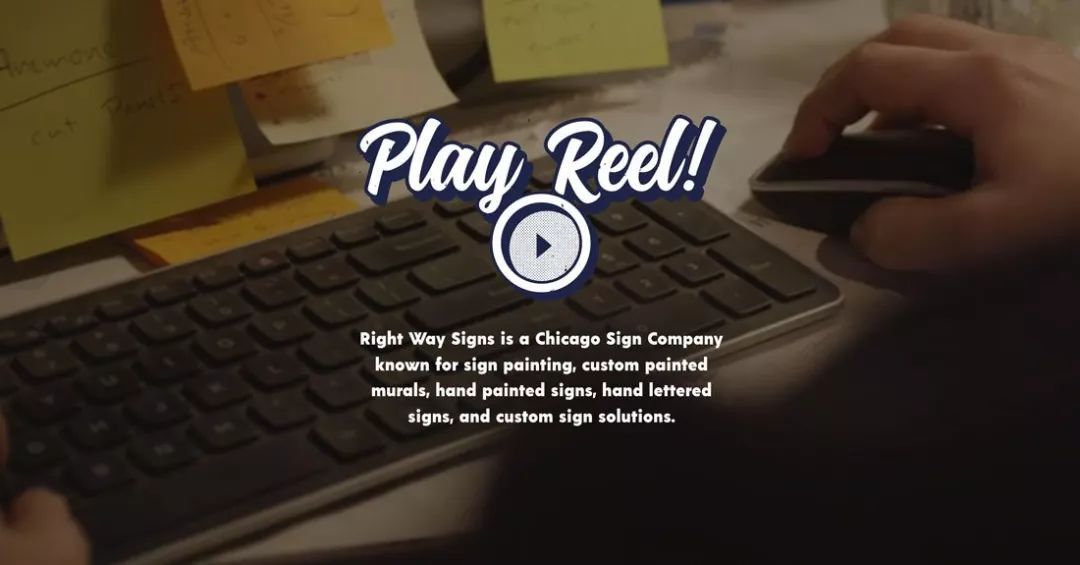
无论你使用什么软件做设计,都不要使用默认的阴影效果,这个经验里面包含了太多血的教训。
正如前文所说,好的阴影特效有着较高的融入度,几乎是「隐形」的。在部署阴影特效的时候,不要为了创建而创建,而是要借助阴影来构建前景文字和背景之间的层次感,这种对比恰到好处即可。
这种「隐形」的阴影设计对于设计师而言通常是不难识别出来的,不过普通用户通常不会太注意到它们。这些柔和的阴影,功能只是用来营造对比。
相对较为硬朗的阴影,会给人以更加复古的感觉,在较粗的、笔触平整的字体背后使用这样的阴影效果会比较好。
2. 使用双重曝光效果
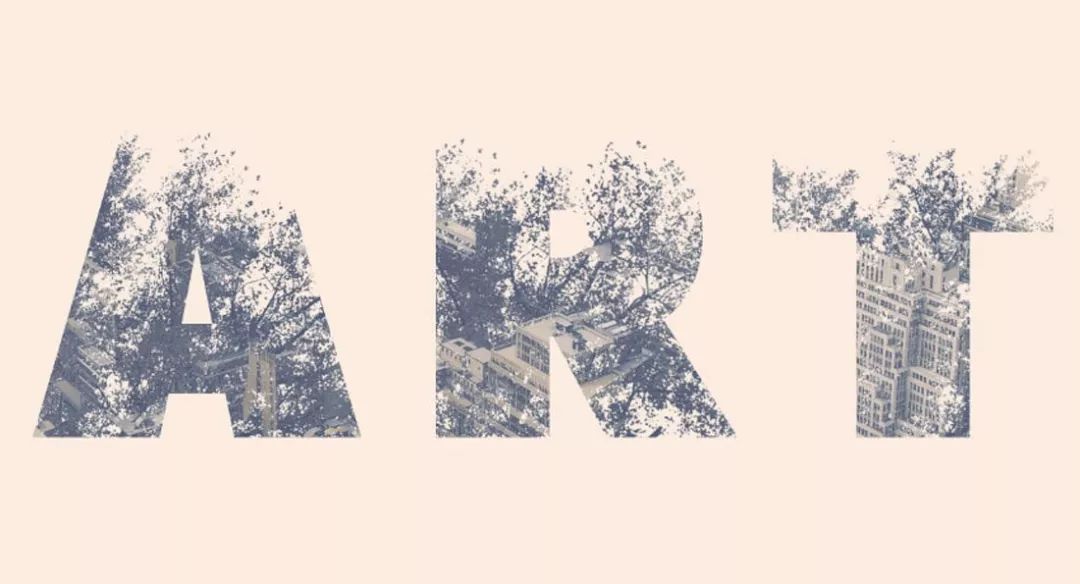
双重曝光效果在网页设计和平面设计当中是非常流行的设计技巧。在文本字体中使用双重曝光效果能够让它看起来复杂而有趣,尤其是在双重曝光的图片选取得比较精妙的时候,效果看起来会非常惊艳。
3. 描边特效
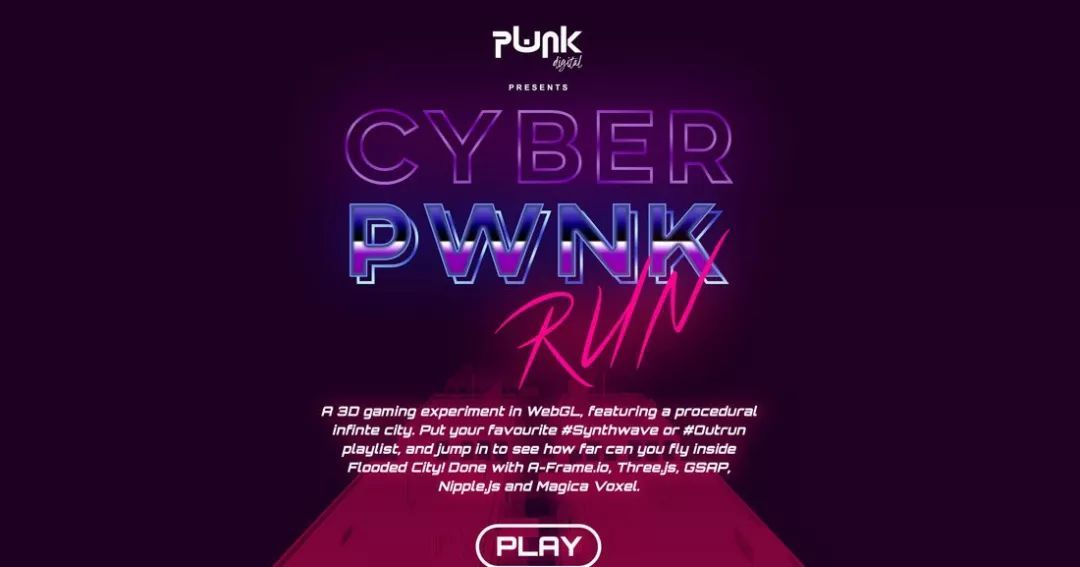
对于较粗的字体使用描边特效,往往能够让字体的轮廓更加清晰,也增加了整体复古的感觉。在上面的案例当中,设计师就借助霓虹色字体和描边特效创造出了独特的氛围。
4. 使用多彩字体
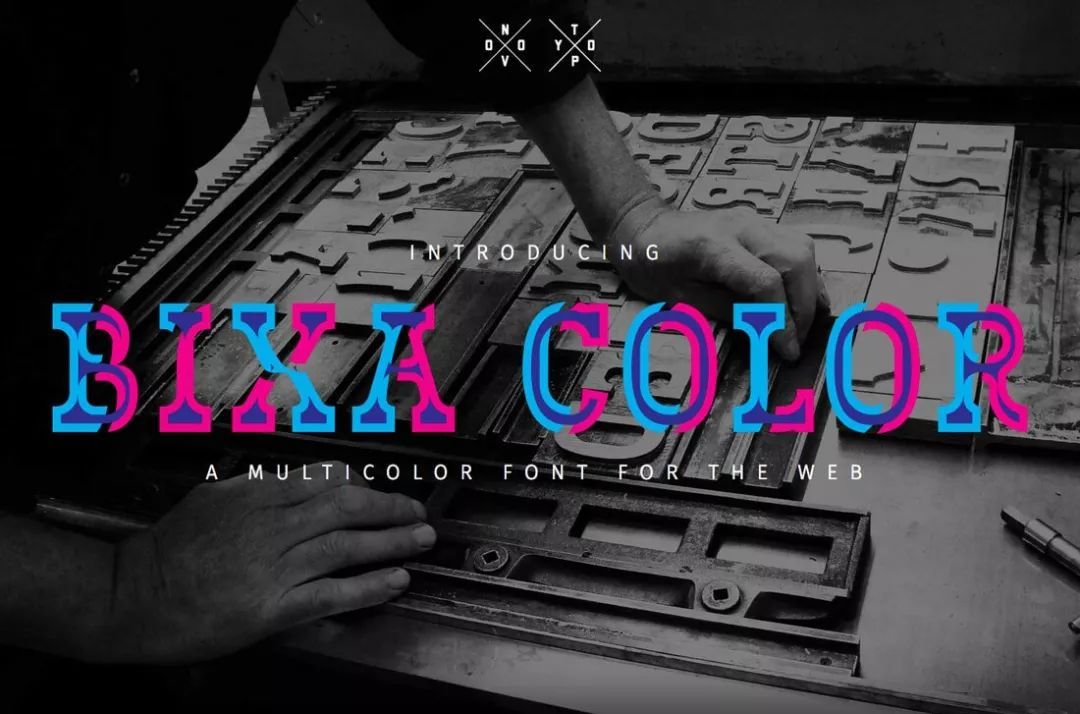
多彩字体本身就包含有多样的色彩属性,甚至含有阴影、渐变、透明度甚至纹理。你可以使用多彩字体来让文本拥有远超传统字体的时髦值。
当大量的色彩共同来构成一套字体的时候,字体本身的视觉吸引力就已经达到极致了。现如今明亮大胆的字体是一种设计趋势,这样的配色本身并不会冒犯用户,因为用户正在越来越适应这样的设计。
当然,在色彩的搭配上需要协调且有目的性。
5. 适当地融入一些动效
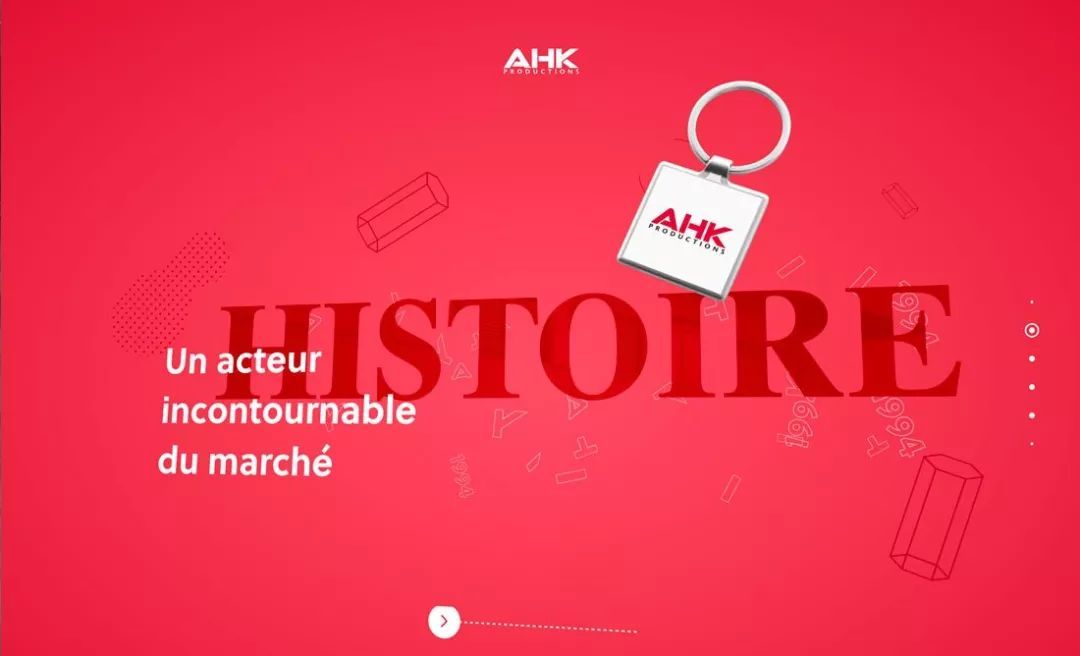
从来都没有规定文本必须是静止的,在网页的文本中加入动效能够提升它的视觉吸引力。
不过,在为文本添加动效的时候,尤其要注意保持文本字体的可读性:
运动轨迹应该是有意识地设计的;
字母的运动不应该太快;
滚动或者自动播放的文本应该可以被停止;
无论屏幕大小,文本内容应该始终保持可读。
6. 模仿一些标志性的元素和特征
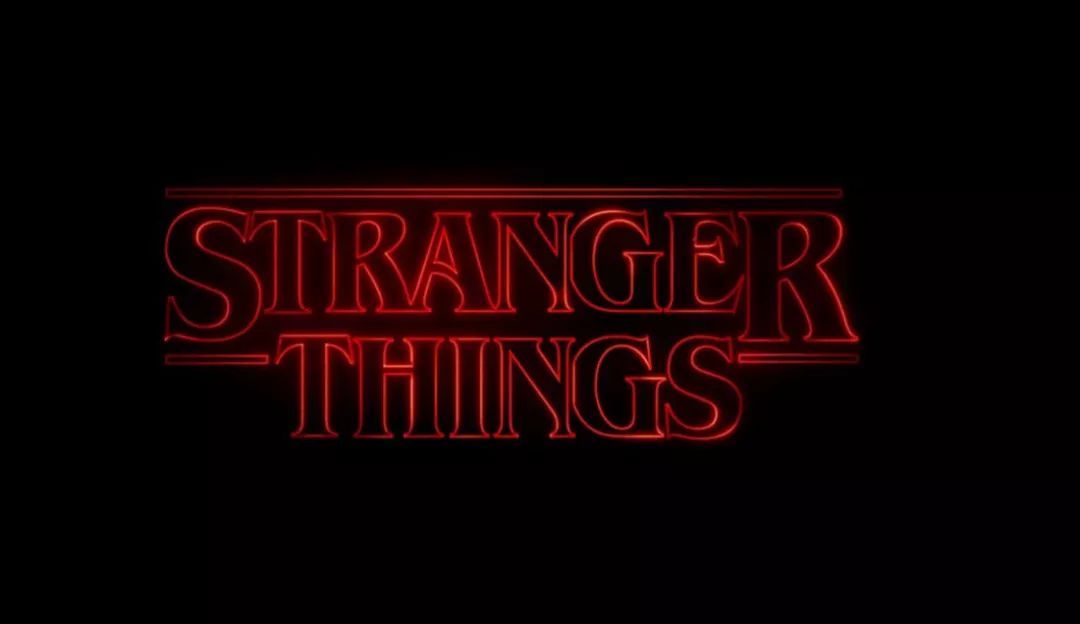
这两年的 Netflix 的热门美剧《怪奇物语》中,就模仿80年代经典的电影,融入了大量当时的元素,创造出让许多影迷共鸣的设计。
最典型的就是霓虹色的运用,充满80年代风情的 LOGO 成为了该剧最具识别度的元素。这种模仿的基础在于近年来80年代复古元素的疯狂流行,以及霓虹色等设计风格的回潮。
在模仿这些标志性的风格和元素的时候,度的把握很重要,恰到好处的模仿让人觉得亲切,而拙劣的复制则会显得很 Low。
7. 引入图形
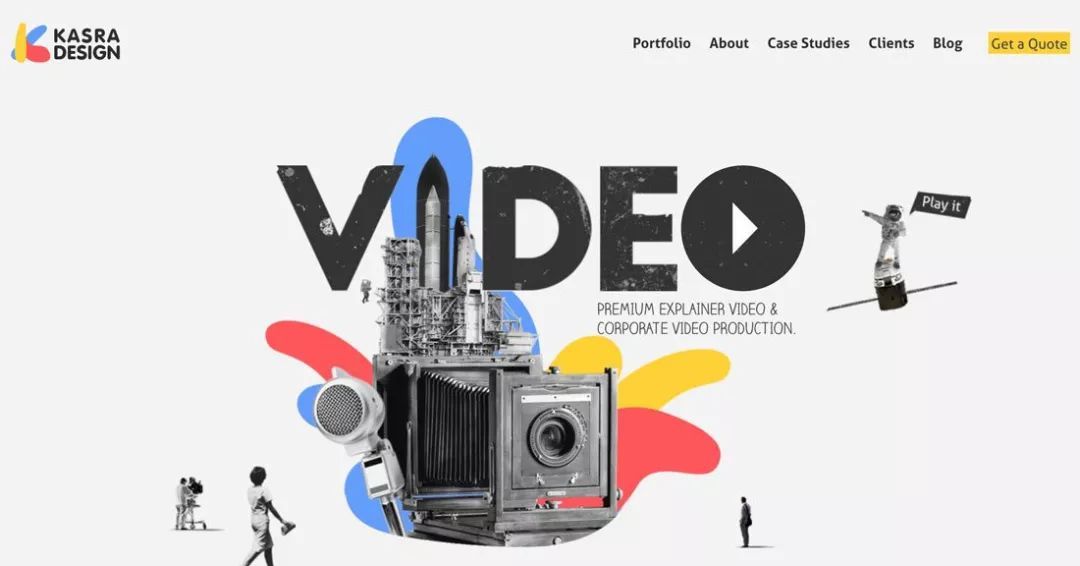
引入图形或者其他的多媒体元素,在文本中加入一些额外的东西,也是不错的手法。使用图形或者其他的元素来替代一个或者多个字母,这样的设计还是很抓人眼球的。
这种技法的诀窍在于,图形的外观要和字母的风格、形状相匹配。很明显,如果不这么做的话,会让内容难以阅读。
在上面的 Kasra Design 的网页当中,视频的触发按钮和图标很好地融合了起来。
8. 增加纹理
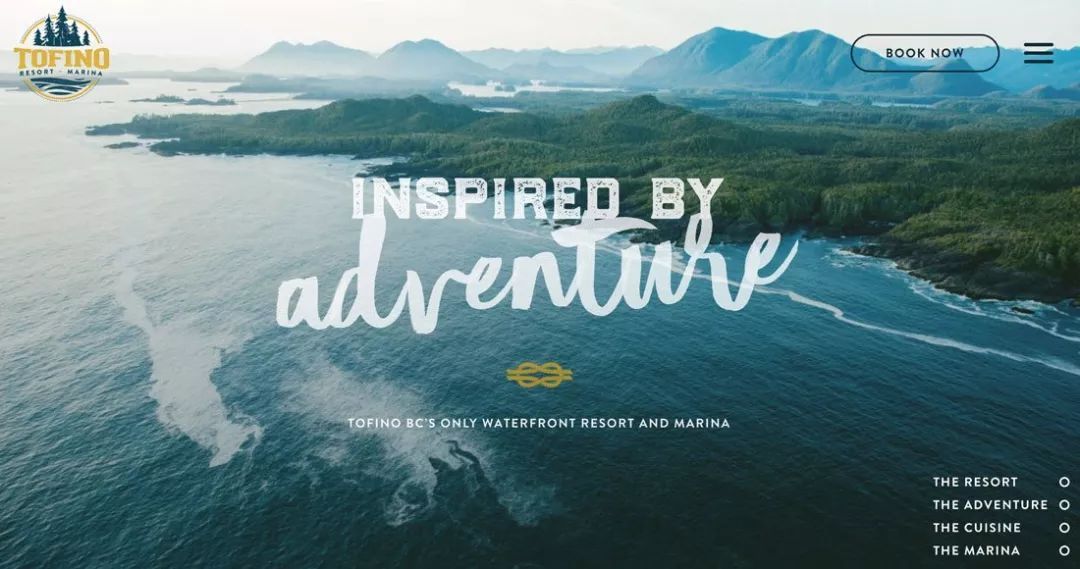
有些字体风格本身就显得复古、粗糙,设计师能够通过自定义增加纹理来强化这种感觉。纹理本身能够让文本更加突出一些,也能够强化文本的质感,营造出独特的氛围。
在上面的案例当中,设计师通过两种不同的方式来赋予文本以纹理:
通过切割出来的细节来赋予文本以纹理;
通过半透明的效果让字体透出背景,从而拥有纹理。
9. 创造自定义的文本字体
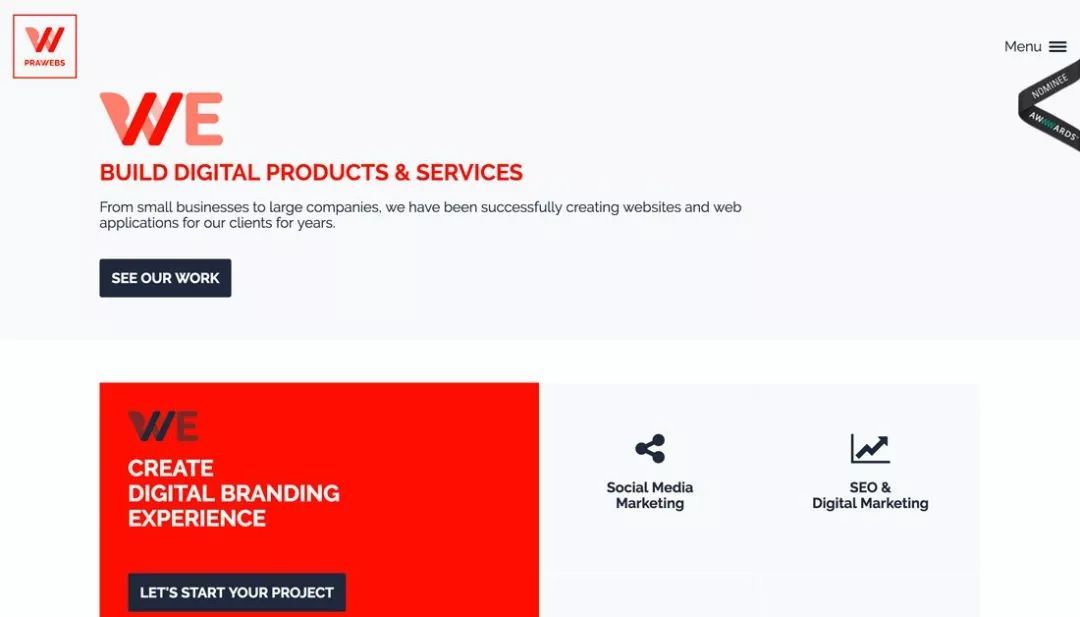
在进行品牌 LOGO 设计的时候,自定义的文本字体是最常见的元素之一。基于特定的字体来进行自定义设计,通过标志性的细节来营造令人难忘的视觉体验,是自定义字体的主要目标之一。
这并不是一件容易实现的事情,自定义文本字体不仅需要足够扎实的技术,而且需要在具体设计的时候,足够小心谨慎。在绝大多数时候,最好是要同专业的字体设计师合作,以达到最好的设计效果。
10. 让字体本身发挥效果
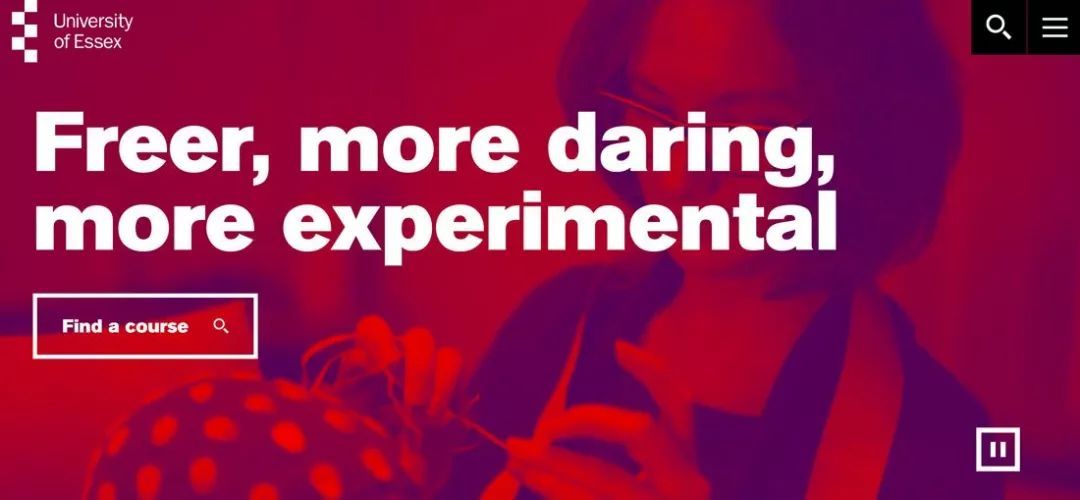
有的时候,最好的文本效果,就是不要加其他任何特效。在形状、大小和色彩具有足够对比度的情况下,文本元素和背景会自然地构成前后景的对比,自然分离。
缺少其他效果的加持,设计师需要精心地控制所有的辅助性的元素,确保所有的元素能够完美的协同工作。加粗字体,深浅对比,是比较合理的组合方式。
The University of Essex 这个网站就在较暗的背景上采用了加粗的白色字体,视觉上足够突出,也足够清晰。
结语
文字特效的使用还需要特别注意设计趋势的存在,过于突出的特效可能会显得过犹不及,而趋势的流行周期也是设计师需要尤为注意的问题。微妙的设计总归是拥有更加持久生命力的。